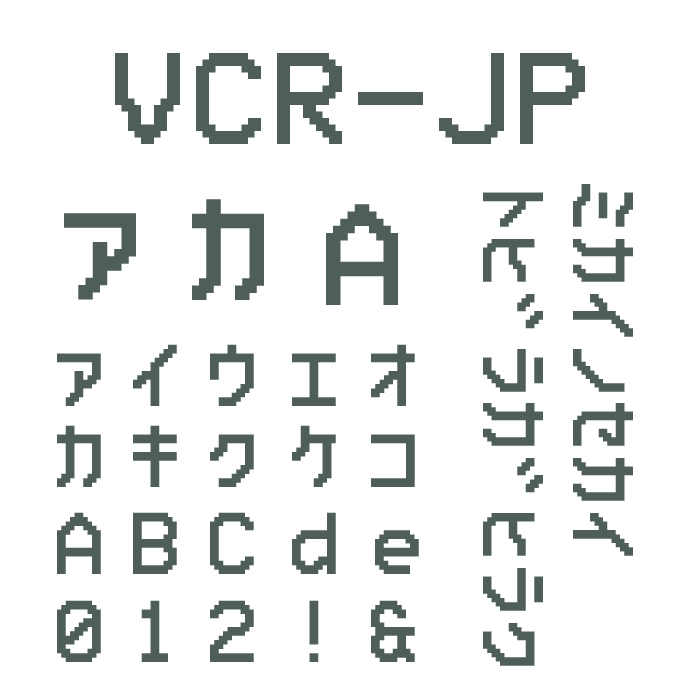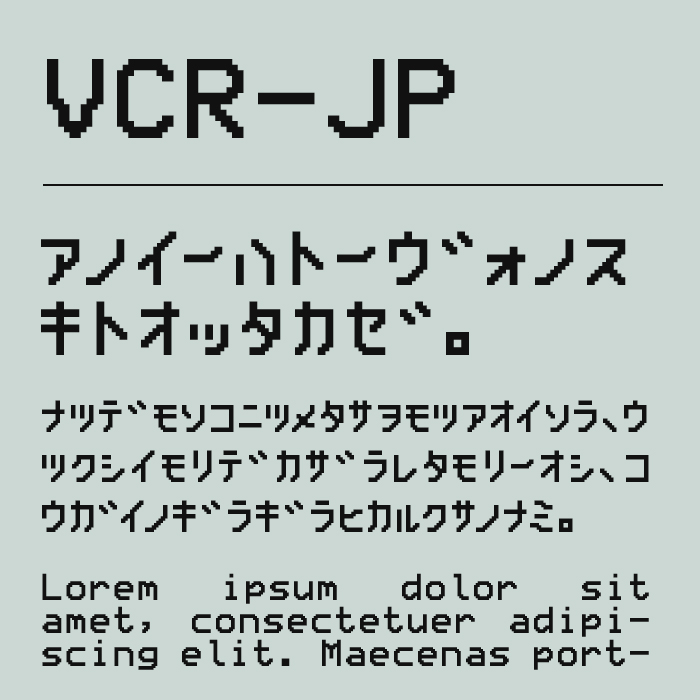
VCR-JP ビデオデッキ風日本語フォントは、昔のビデオデッキに使われていたようなドットフォントとして制作されたフォントです。
1980〜90年代のアーケードゲームやPCの世界観を連想させる文字デザインは、懐かしさと遊び心があり、ノスタルジーな味わいが可愛らしいフォントです。
ビデオデッキ風なパロディデザインはもちろん、ゲーム実況や動画の字幕、ノスタルジックなポスターなど幅広く活用でき、ドット表現で親しみやすさを演出したい場面におすすめのフォントです。
収録文字は、カタカナ・アルファベット・数字・記号が収録。